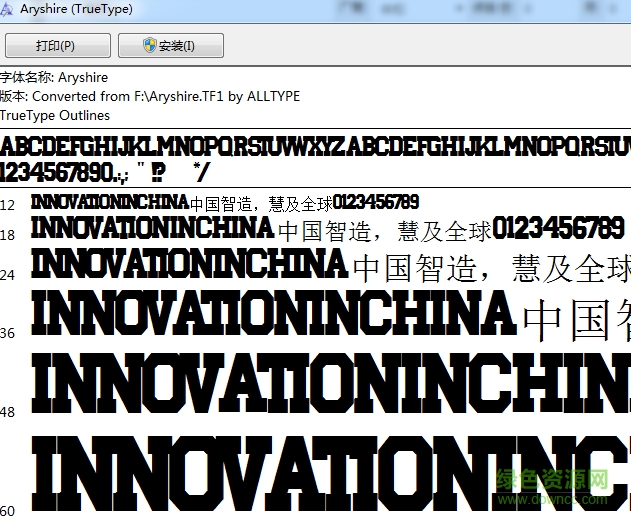
Aryshire字體是一款極具個性的英文字體,字型線條非常均勻,字體正常正規(guī),適用于比較正規(guī)的場合。有喜歡的朋友可以來綠色資源網(wǎng)免費下載使用!
Aryshire字體是英文字體庫中的一款字體,該字體十分內(nèi)斂,適用于各類文件的打印,如果您需要的話,就趕快來綠色資源網(wǎng)下載吧!